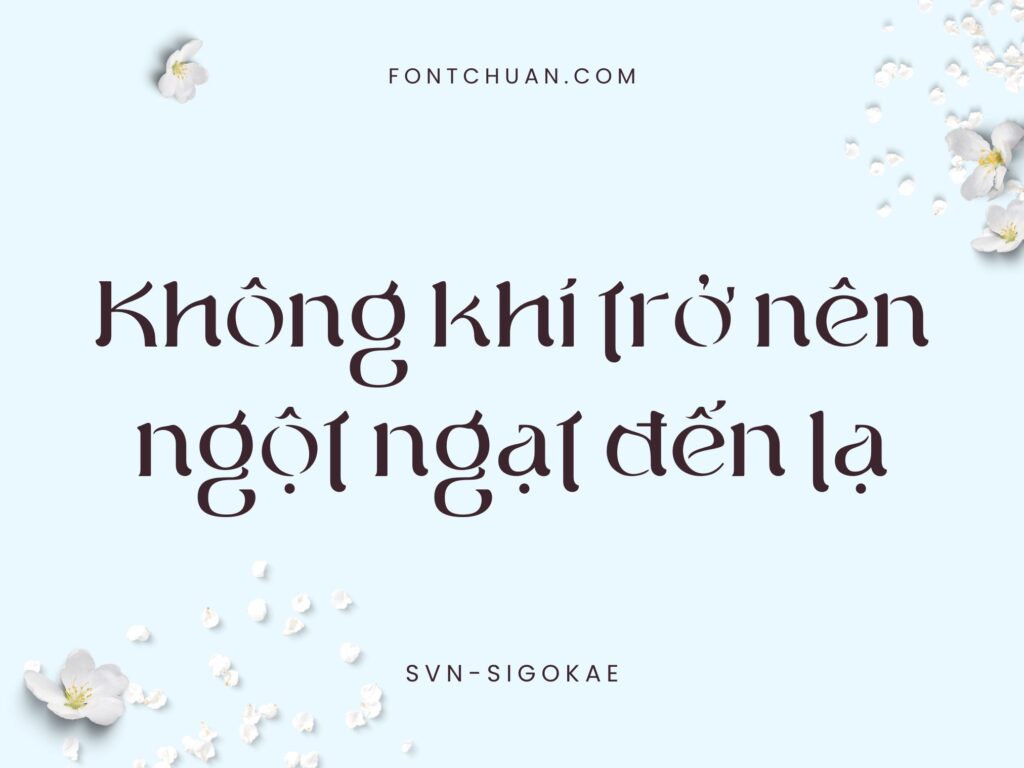
Font SVN Sigokae Việt Hóa
Tác giả Font: Glyphstyle
Font SVN Sigokae là phiên bản Việt hóa của kiểu chữ Sigokae, được thực hiện bởi STYLEno.1 Fonts. Sigokae là một Font Decorative sans-serif mang phong cách Nhật Bản, được thiết kế bởi GlyphStyle. Font này có hình dạng đơn giản kết hợp với các đường cong đặc trưng và sáng tạo, tạo nên cảm giác giống như các ký tự Nhật Bản. Sigokae bao gồm đầy đủ các ký tự chữ hoa, chữ thường, chữ số và các ký tự đặc biệt, hỗ trợ đa ngôn ngữ, phù hợp cho nhiều mục đích sử dụng khác nhau như thiết kế logo, tiêu đề, bao bì sản phẩm và các ấn phẩm truyền thông.
SVN Sigokae lý tưởng cho các dự án thiết kế yêu cầu sự độc đáo và sáng tạo, như thiết kế logo, tiêu đề, bao bì sản phẩm và các ấn phẩm truyền thông. Các ngành nghề như quảng cáo, công nghệ và giáo dục có thể tận dụng font này để tạo điểm nhấn trong thiết kế. Ngoài ra, font cũng thích hợp cho các sự kiện như Tết, Giáng sinh, Halloween và các lễ hội khác.